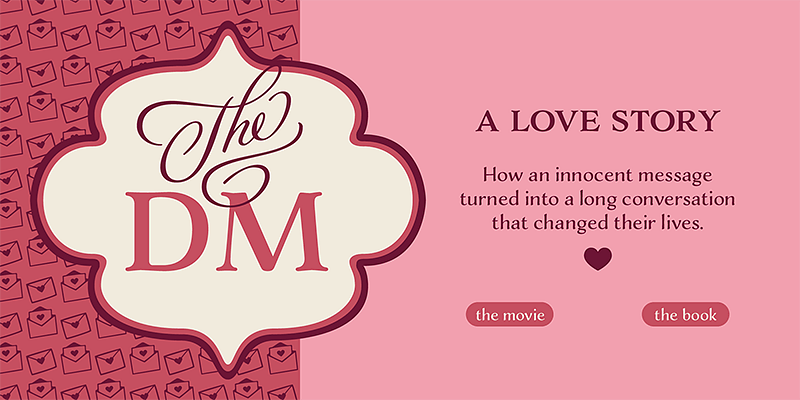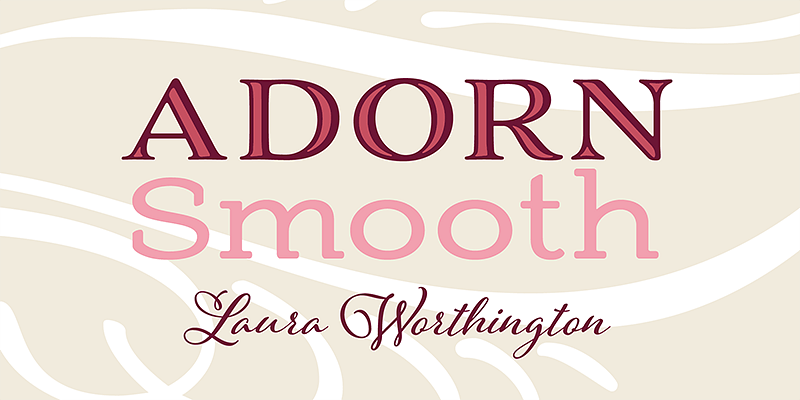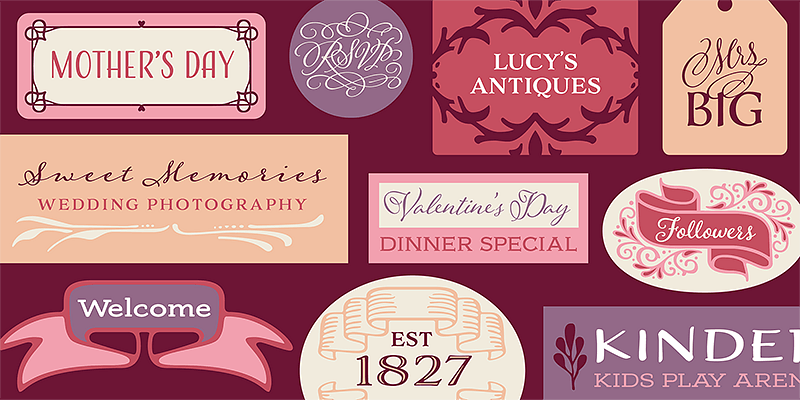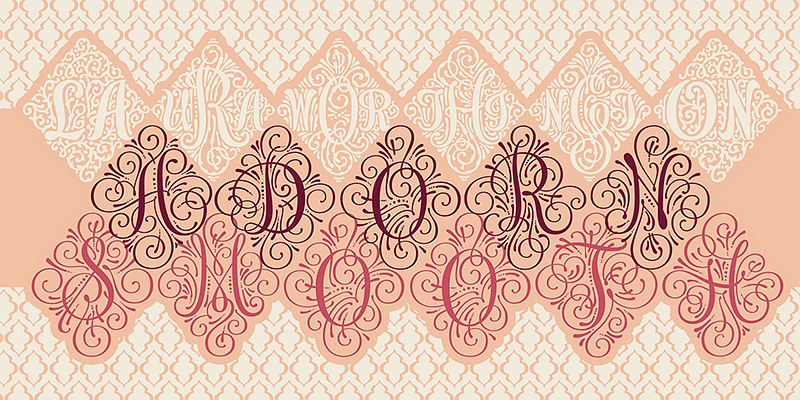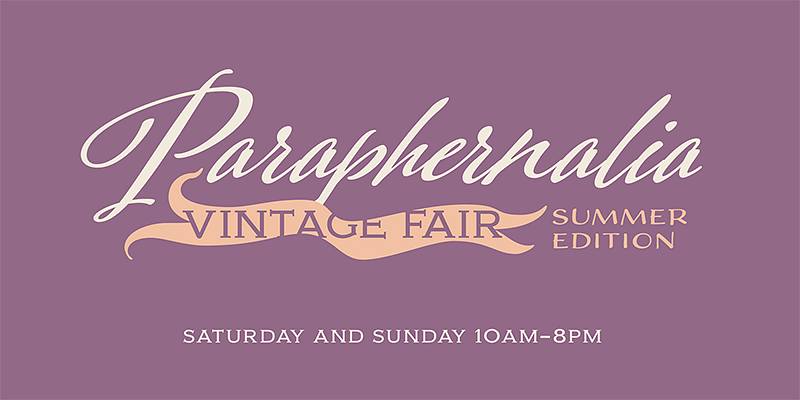
Bei Laura Worthington Design entdecken Sie eine wunderschöne Auswahl an exquisiten Schriften, die mit künstlerischem Gespür und sorgfältiger Handwerkskunst handgezeichnet wurden. Lauras Schriften basieren hauptsächlich auf ihrer Handschrift und Kalligraphie und spiegeln ihren eigenen, unverwechselbaren Design-Ansatz und ihre Liebe zum Detail wider. Verspielt und lässig oder elegant und raffiniert – die unglaublich vielseitigen Schriften der preisgekrönten Designerin Laura Worthington eignen sich perfekt, um jedem Projekt ein wenig Pomp und Eleganz zu verleihen.